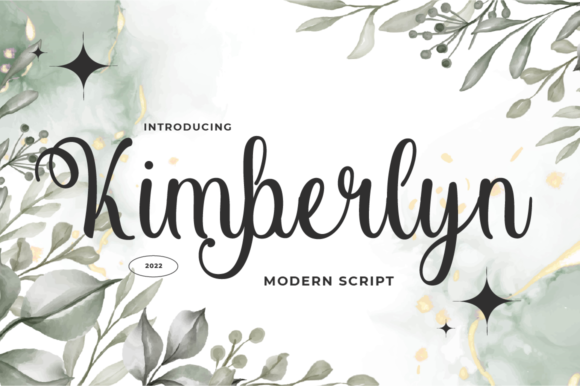
Kimberlyn
Việc tìm kiếm các thành phần thiết kế phù hợp có thể là một thách thức, nhưng Kimberlyn cung cấp một bộ sưu tập đặc biệt giúp nâng tầm công việc của bạn ngay lập tức.
Được chế tác với độ chính xác cao, Kimberlyn cung cấp các vector sạch, kiểu chữ mượt mà và giấy phép thương mại để bạn yên tâm.